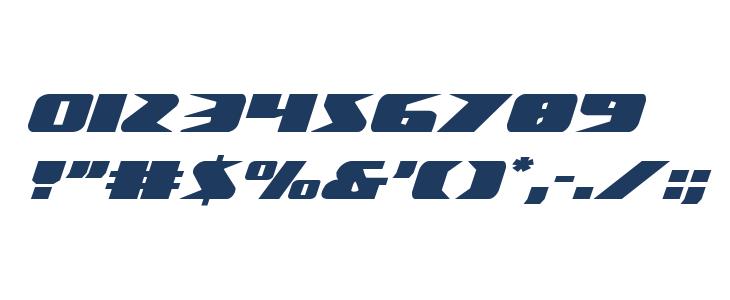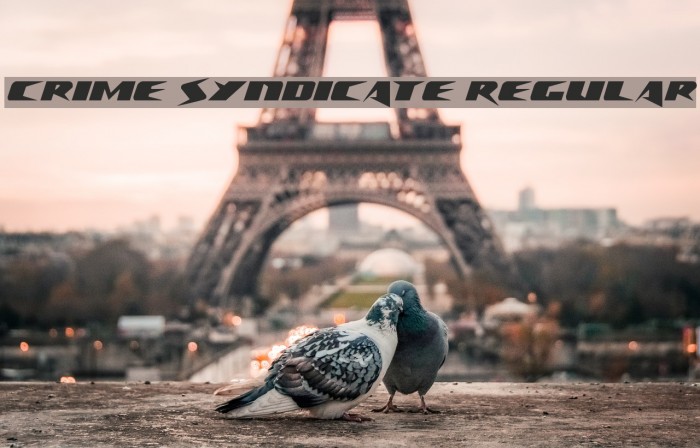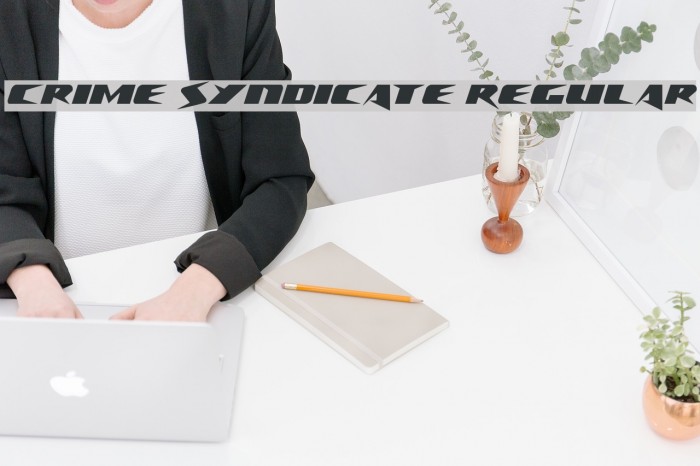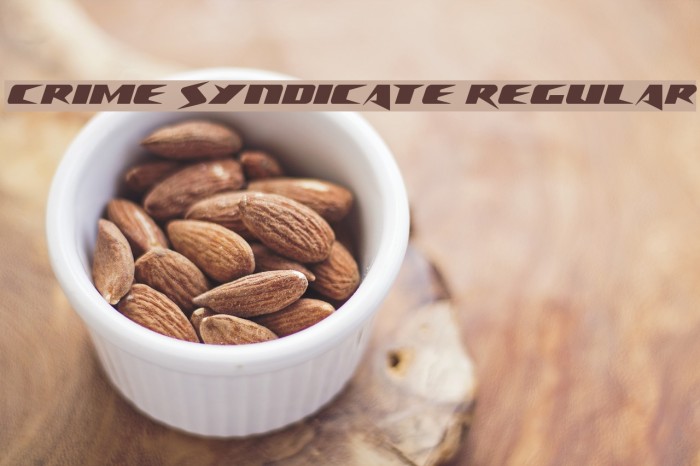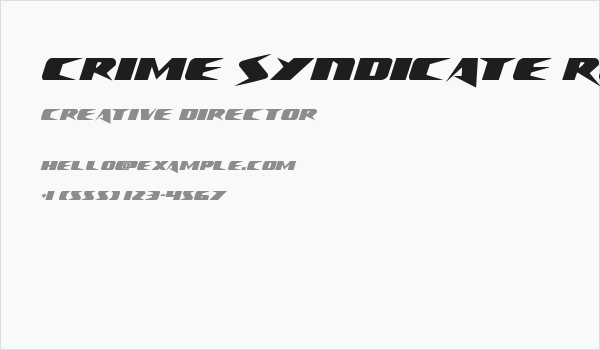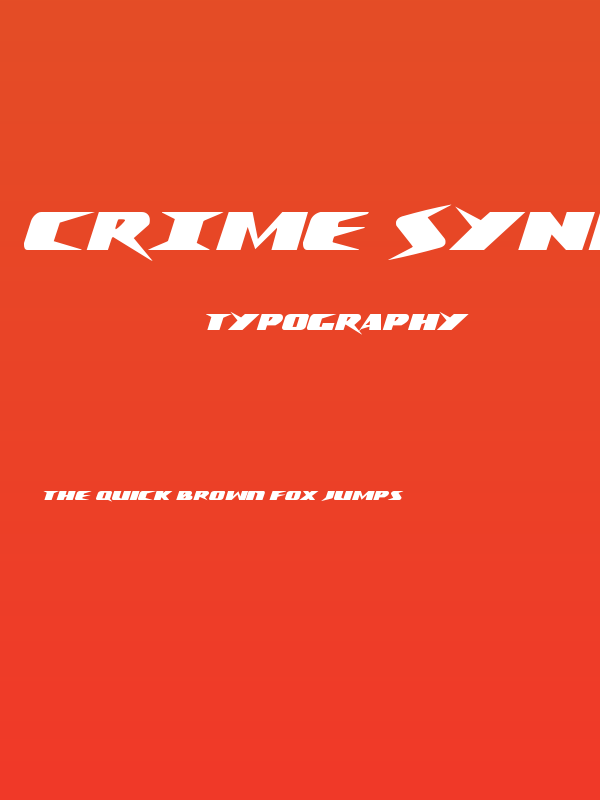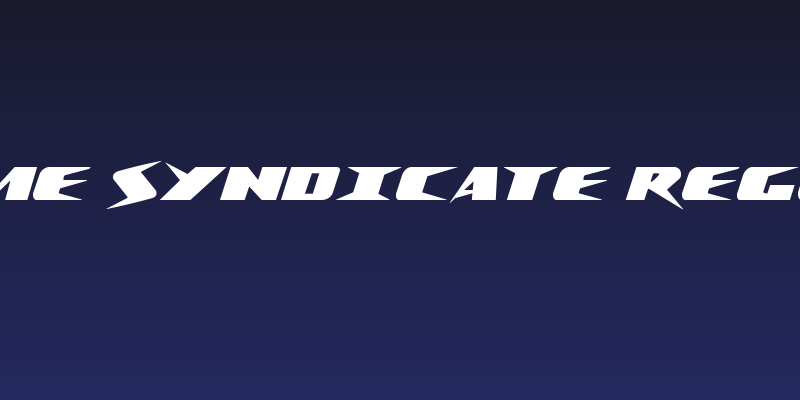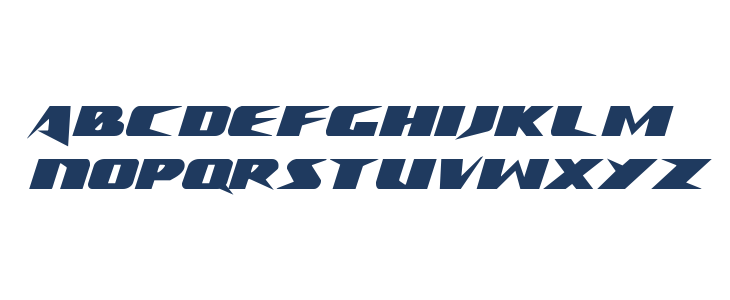
Crime Syndicate Regular Font
| 全体的なスタイル | Futuristic, Aggressive |
| おすすめプロジェクト | Ideal for video game titles, movie posters, branding for tech companies, or any project needing a bold, futuristic look. |